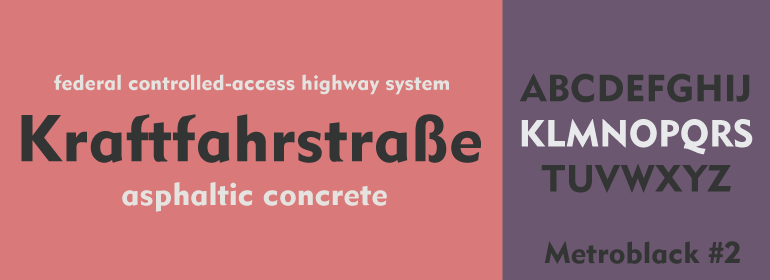
Metroblack™ #2
Metroblack™ #2,这款字体结构工整、笔画清晰,兼顾美观与易读性,适用于标题、正文、海报、包装、LOGO 等多种场景。字形优雅稳定,风格百搭耐看,适配日常排版与创意设计,让文字呈现更舒适、更具质感。Metroblack™ #2一笔一画,皆是细节,以均衡的比例、流畅的线条打造舒适视觉体验,字形端正大气,风格简约现代。无论是商业设计、品牌宣传还是日常排版,都能轻松驾驭,让文字更有格调与力量。Metroblack™ #2字体下载。
字体品牌: Linotype(Monotype) 设计师:Dwiggins,William A. 字体分类:无衬线体 字体属性:外文 字符集:Unicode 发布时间: 2018